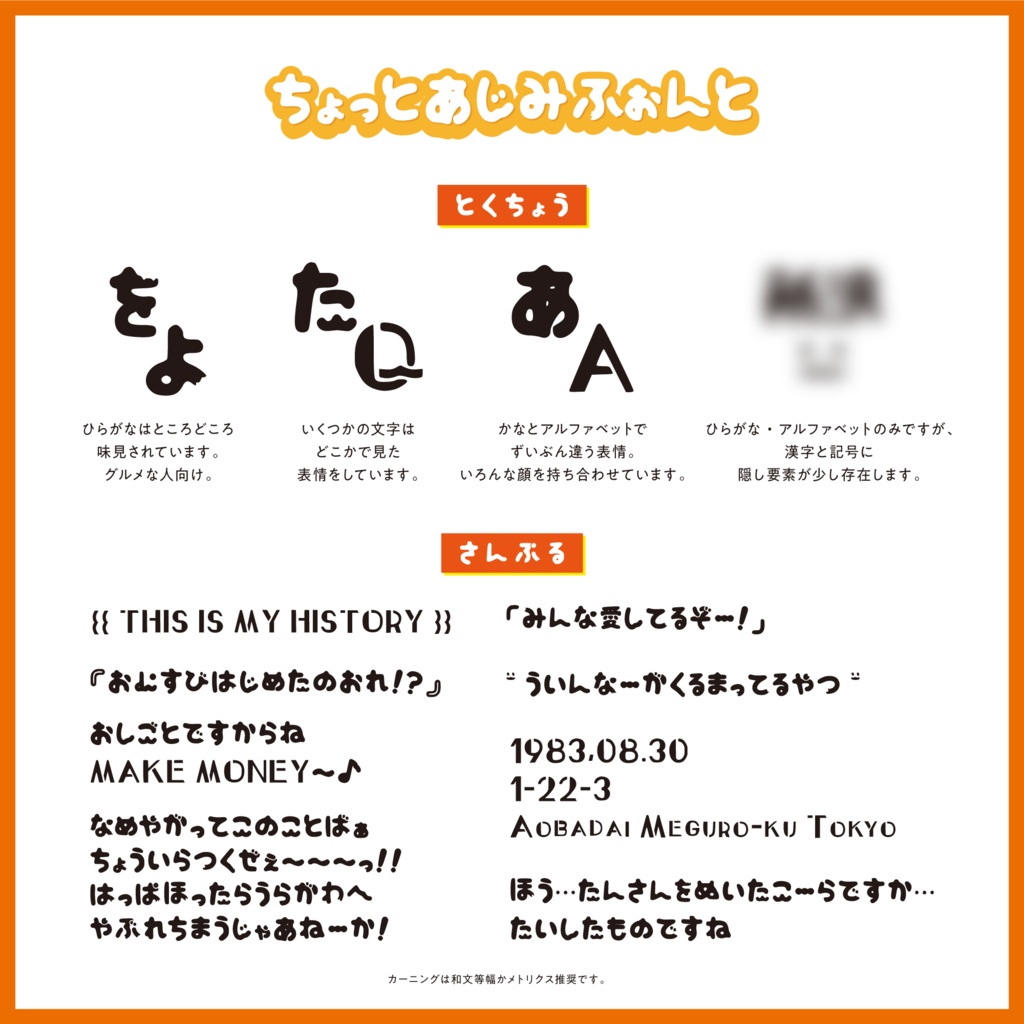
ちょっとあじみフォント
商用使用・個人使用、使用用途を問わずすべて無料でご利用いただけるフォントです。 半角英数字、ひらがな、記号、一部漢字(35文字程度)を収録しています。 イメージ元の印象により、アルファベットとひらがなで大きく表情が変わるのが特徴です。 ひらがなの一部には味見をされたようなかじり跡があります。 漢字は隠し要素としてお楽しみください。 同梱ファイル内のreadmeに目を通してからお使いください。 フォントファイルを内包するコンテンツの制作も無料で利用可能です。 このフォントの使用によるトラブル、不利益には一切の責任を負いませんのでご了承ください。 『ちょっとあじみフォント』の著作権は制作者に帰属します。 ・禁止行為 再配布、当フォントを改変・加工して新規フォントとして配布する行為 公序良俗に反する媒体での使用